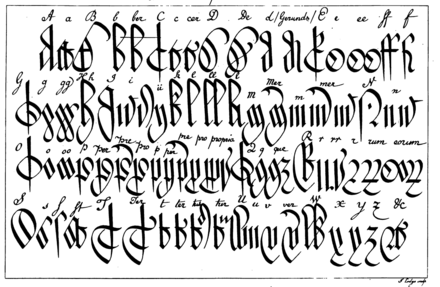
Кириллические рукописные шрифты в дизайне сайта
Нравятся рукописные шрифты, но считаете что они не впишутся в дизайн вашего сайта? Несмотря на все свои витиеватости и завитушки, рукописные шрифты могут отлично смотреться в заглавии, в тексте или в дизайне логотипа. Они отлично сочетаются с другими шрифтами и притягивают к себе внимание даже если выступают в роли второго, дополнительного шрифта.
А для того, чтобы вы в этом удостоверились, мы сделали подборку дизайнов, в которых кириллические рукописные шрифты очень органично смотрятся в дизайне.
Рукописные шрифты в дизайне
Посмотрите, как можно использовать рукописные шрифты в оформлении страниц сайтов или логотипах.
Меню на сайте кондитерской
Надпись на Главной странице и буквенный логотип сайта пекарни
Буквенный логотип магазина органической еды
Второй шрифт в дизайне сайта ресторана
Рукописный шрифт в дизайне гастрономического интернет-магазина
Заглавный шрифт в Keynote презентации
Бесплатные кириллические рукописные шрифты
Вдохновившись идеями для использования рукописных шрифтов, предлагаем вам выбрать один из предложенных ниже и смело использовать в своём проекте.
Рукописный шрифт обязательно добавит уникальности вашему сайту и понравится пользователям. Он сразу привлечет внимание среди шрифтов семейства Sans Serif.
Кириллический шрифт Brush Flair Cyr
Кириллический шрифт Intro Script R h3 Base
Кириллический шрифт LainyDay
Кириллический шрифт Angelface [Rus by me]
Кириллический шрифт Poetica Chancery
Кириллический шрифт BetterTogether-Script
Бывают ситуации, когда пользователям нужен уникальный рукописный шрифт для Word. Этот шрифт в тексте отличается от остальных шрифтов тем, что он имеет вид рукописи. Как будто его написал от руки человек. Зачем он вообще нужен, если можно писать любые документы в Ворде со стандартным шрифтом?
Например, в школьных заведениях или в Институтах задают домашние задания, которые нужно выполнить написав их от руки. А если преподаватель заметит, что эта работа была сделана с помощью компьютера, по этой причине может понизить оценку. Или эти шрифты хорошо подойдут для какой-либо книги.